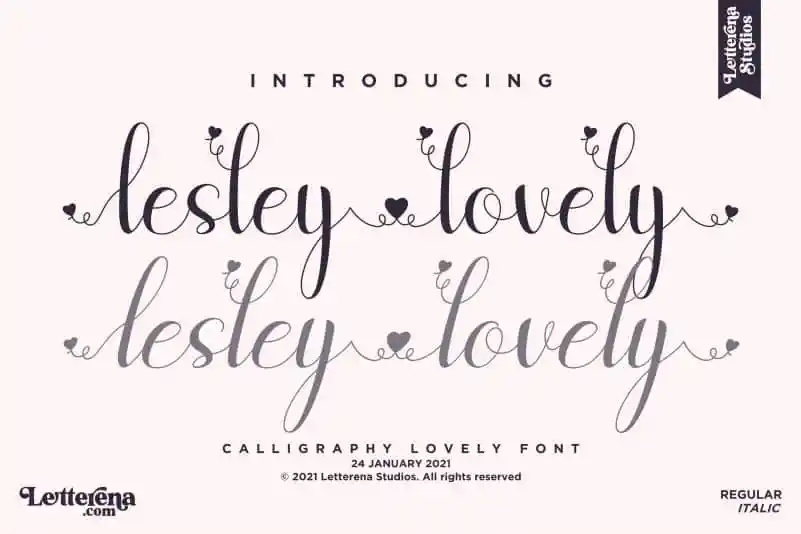
Lesley Lovely Calligraphy Font – Fonte Grátis
Lesley Lovely Calligraphy Font
A Lesley Lovely Calligraphy Font é uma opção perfeita para quem busca um toque romântico na hora de criar designs delicados. Desenvolvida pela Letterena, esta fonte calligráfica script é adequada a uma ampla variedade de projetos, desde os mais simples até os mais elaborados, como selos e embalagens, ilustrações, cartas personalizadas ou até mesmo sobreveio para fotografias. Seja para dar um toque delicado em uma camiseta customizada, enfeitar um pacote com etiquetas criativas, criar adesivos de papelaria de evento especial, ou simplesmente deixar seu trabalho de design mais amável e pessoal, a Lesley Lovely Calligraphy Font é ideal. É uma fonte versátil para quem busca personalidade e elegância em seus projetos. Estar na categoria de Fonts Script também significa que essa fonte pode complementar um número impressionante de tipos de outros materiais e estilos, tornando-a uma opção excelente para aqueles que querem dar vida a suas ideias. Através da Lesley Lovely Calligraphy Font, você terá a capacidade de expressar seu design de maneira única, criando designs perfeitos para o seu próximo projeto pessoal ou profissional.